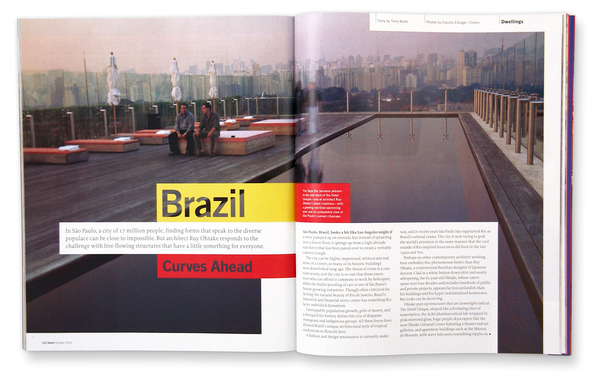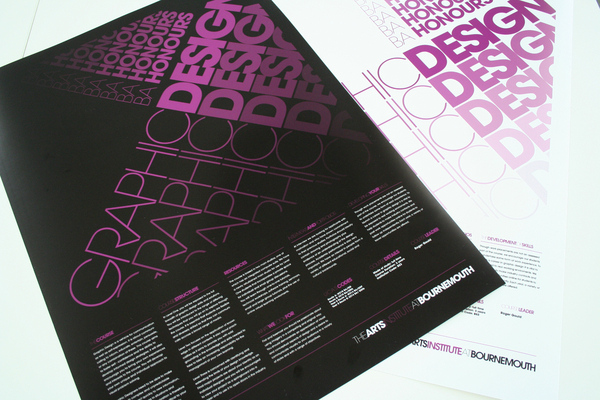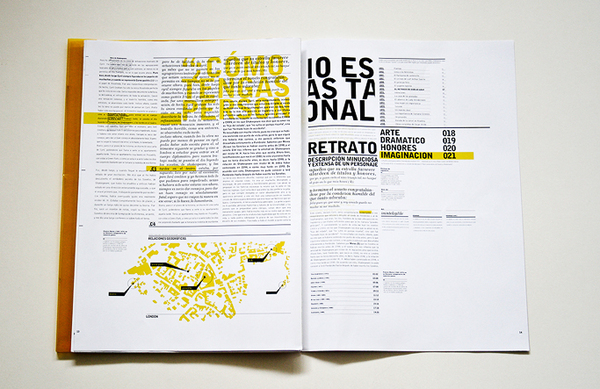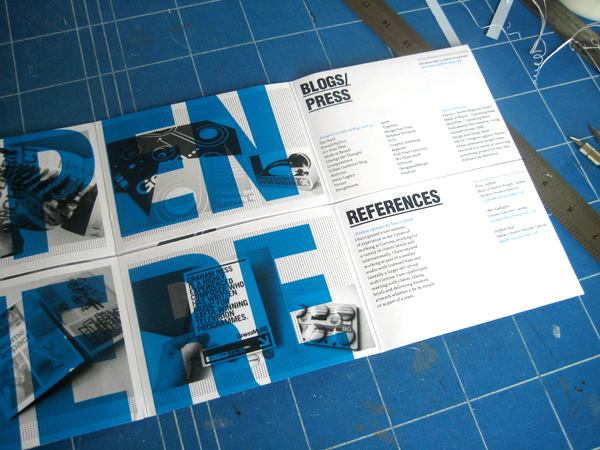
11 Consejos esenciales tipografía en impresos
La tipografía es una enorme parte del diseño y el diseño es una enorme parte de los tipos. No puedes simplemente arrojar texto en una página, tiene que estar bien colocada y organizada de una manera limpia para agregarle a la información que es presentada. Aquí hay 11 consejos tipográficos para ayudarte a transmitir correctamente la información que es impresa.
1.- Usa una composición basada en una rejilla*.
La rejilla es la estructura subyacente de casi todo lo que harás en el diseño, especialmente en la impresión. Ella te ayudará a crear una composición limpia y agradable.
Las rejillas son simplemente una estructura de columnas y filas. Típicamente, cuando alguien menciona una rejilla, uno puede pensar incluso en líneas y columnas, todas del mismo tamaño. En la impresión no querrás que todo sea del mismo tamaño. Una variación del tamaño es requerida para una buena composición bien estructurada. Un diseño estándar consiste en una o dos columnas, pero sé original y usa tres, cuatro o hasta cinco columnas. Recuerda que esas columnas necesitan encajar en la página, y cada vez que agregas una nueva columna tu tienes que reducir las otras columnas.
Esta página es un excelente ejemplo de una composición basada en una rejilla. Usa una rejilla muy compleja para organizar todos los tipos y elementos gráficos en un una composición leíble y organizada. También nota, la rejilla no está perfectamente definida, algunos objetos fluyen fuera de los bordes.
2.- Alineación.
Hablando de composición. También hablaré de la alineación. La alineación es una opción más que tiene un fuerte impacto en la estructura . Para una composición de impresión más estándar, es obvio que el cuerpo del texto debe estar alineado a la izquierda Para titulares la mayoría de la gente puede decir que necesita estar centrada, pero el texto de los titulares puede tirar la composición. La alineación izquierda es casi siempre la manera de hacerlo, especialmente con elementos de texto en bold. La alineación derecho también puede funcionar. Ocasionalmente, una página completa puede funcionar alineada a la derecha, pero muchas veces no se verá bien. Usar alineación derecha en un texto más pequeño tal como una nota a pie de página o en una leyenda puede funcionar con una composición alineada a la derecha.
Si tu cuerpo de texto está alineado a la izquierda, sé consciente y haz todo lo demás en la página también esté alineado a la izquierda. El factor más importante en el alineado es estar seguro de hacer que todo esté acomodado en el mismo lugar. Es aquí cuando tu retícula estra en la jugada. Cada objeto de texto debe estar a la misma distancia desde la derecha (o la izquierda).
3.-No te restringas al papel.
El tamaño del papel en el que estás imprimiendo puede ser un verdadero problema algunas veces, porque es difícil encajar todo texto en la página. La solución es salirse de la página. Todo el texto, no tiene que estar dentro de las pequeñas restricciones de la página, tú puedes dejar que el texto  fluya fuera de la página ¿A qué me refiero? En logar de acomodar todo el texto, corta partes permitiendo que el texto fluya fuera de la página, Si cortas una parte pequeña de una carta o una palabra, la gente aún entenderá el mensaje, y tendrás más espacio en blanco. Sé cuidadoso de no cortar muy feo. Mantenlo en un punto donde el texto aún pueda leerse de la misma manera como si uno pudiera leerlo si estuviera completo en el papel.
Esta composición se extiende de la página, pero aún es completamente leíble. También usa una buena repetición, de la cual hablaré después.
4. Espaciado, Márgenes, Kerning e Interlínea.
Usando un buen espaciado y márgenes perfectamente medidos es probable uno de los aspectos más importantes de la impresión y la tipografía. Incluso el espacio más pequeño puede afectar cómo alguien ve el diseño.
El punto de qué es lo que estás haciendo es el contenido. Entonces usa algún tiempo en la legibilidad. Échale una mirada al kerning, el espacio entre las letras individuales y la interlínea, el espacio entre las líneas bases del texto. La interlínea y el kerning son los aspectos más importantes del cuerpo del texto. Si la interlínea es demasiado grade, puede distraer porque hay demasiado espacio en blanco. Haz la interlínea demasiado pequeño y el lector estará restringido intentando leer el texto.
5. Contrastes
Los colores y sus contrastes a veces pueden ser difíciles. Es una de esas situaciones cuando puede lucir verdaderamente bien o de plano no funcionar. Como con el kerning y la interlínea, malos contrastes pueden hacer el texto ilegible. Encontrar el balance perfecto para el cuerpo de texto es desafiante; necesita ser lo suficientemente fuerte para ser visible, pero no tan fuerte que se vuelva distractor.
El contraste es otra técnica para definir los titulares y otros objetos importante, El nivel de contraste puede ayudar a hacer saltar un objeto o hacer que un objeto sea más sutil. Usa un fuerte contraste para textos titulares que quieras que sean notados de manera inmediata.
En cuanto al tema del color. Mencionaré el uso de colores inversos para llamar la atención al texto. Por ejemplo, en lugar de usar texto negro sobre blanco usa texto blanco sobre negro.
6. Objetos yuxtapuestos**.
Acabo de mencionar que deberías apegarte a una composición de rejilla. Bueo, mentí. DEBES usar una composición de rejilla, pero no debes restringirte a una rejilla perfecta. En lugar de eso, intenta yuxtaponer texto y elementos gráficos.